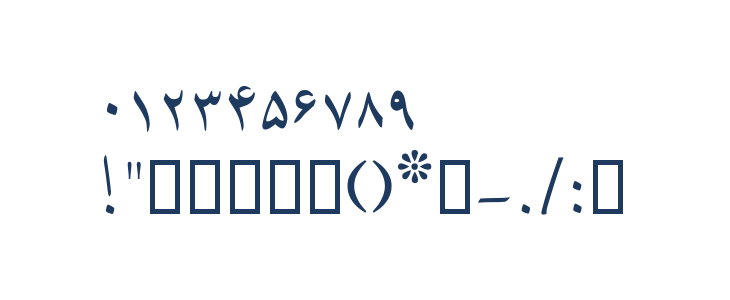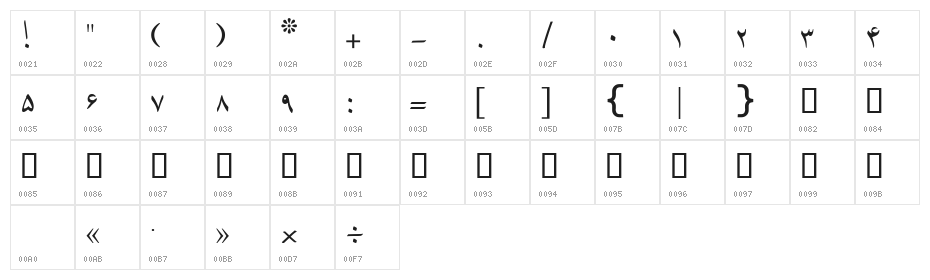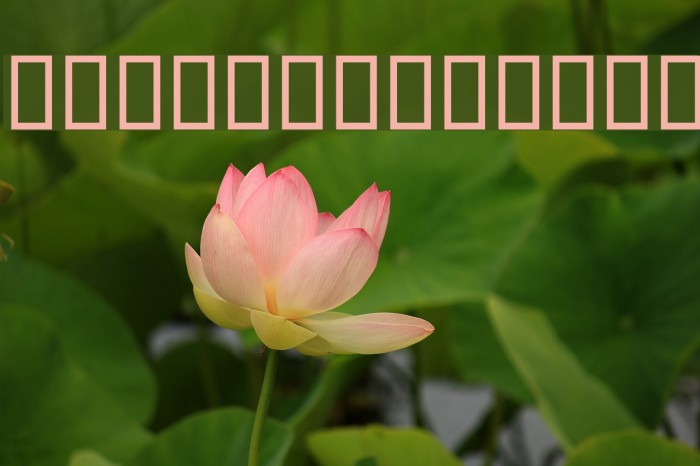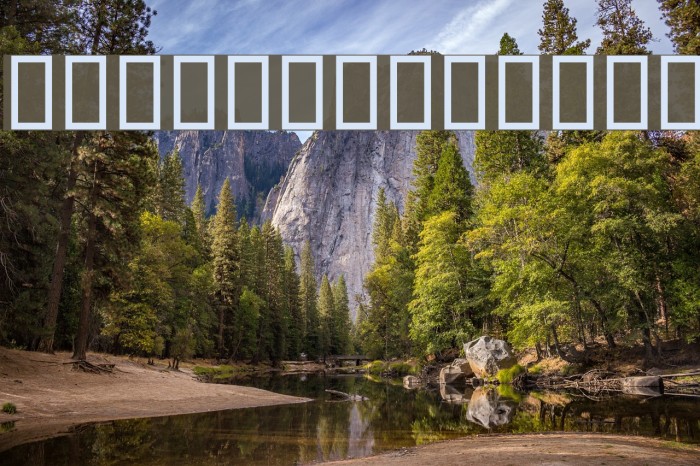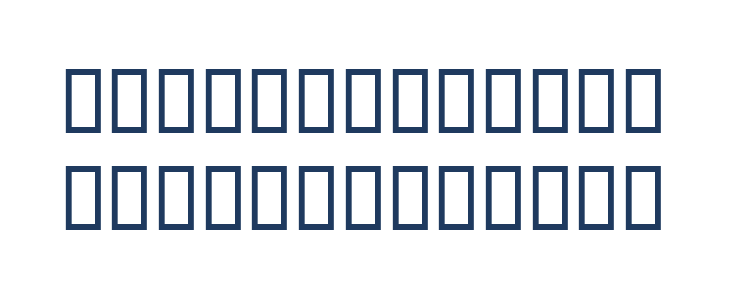
Kabul Type Font
گالری فانت فارسی پژوهش آريانا - only compatible with Farsi and Arabic
| Stile generale | Artistic, Creative |
| Caso d'uso | Logos, Invitations, Artistic Posters |
| Progetti proposti | Ideal for invitations, greeting cards, artistic posters, and branding materials that require a personal touch. |